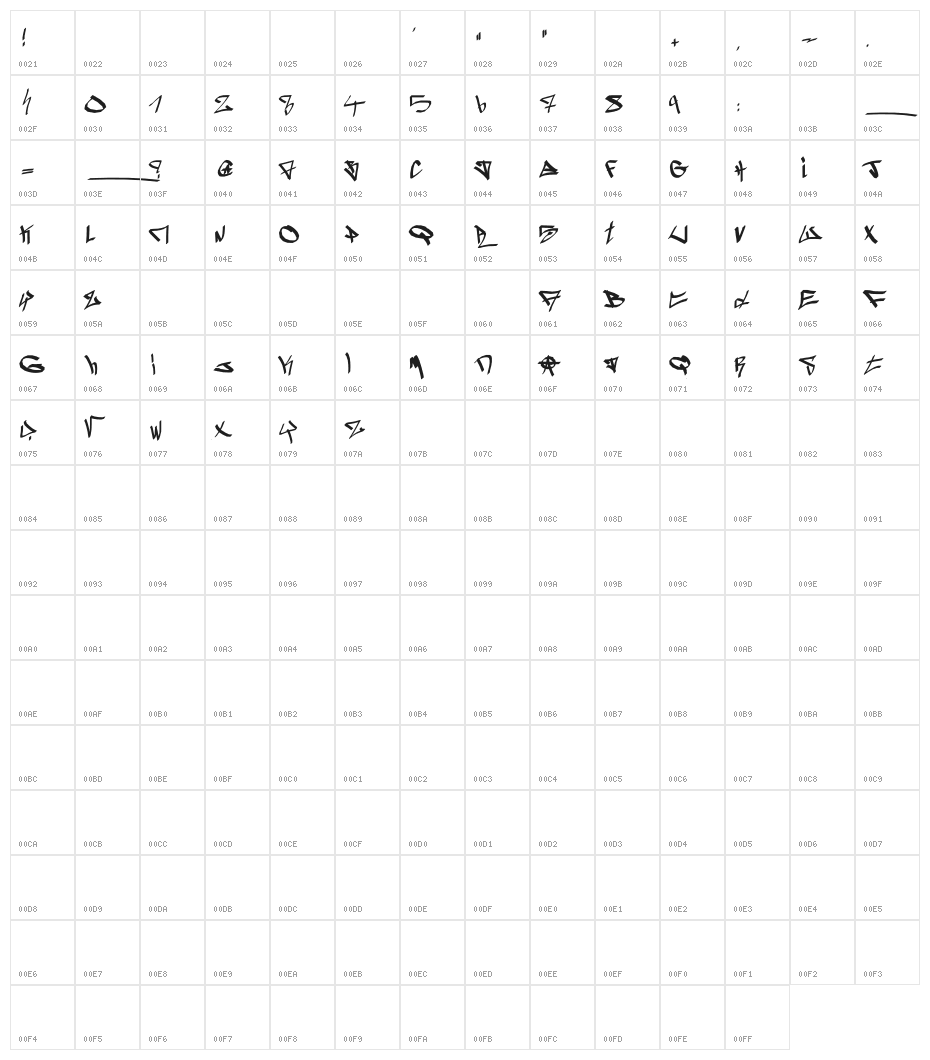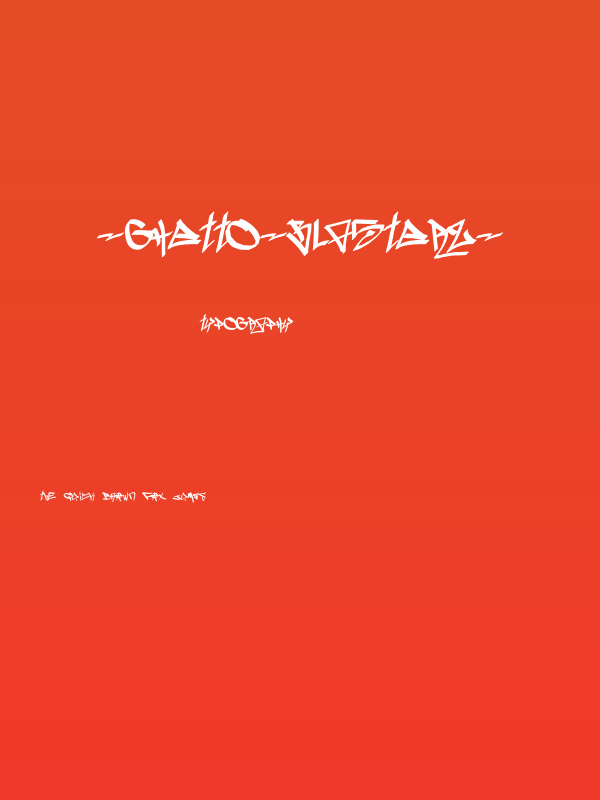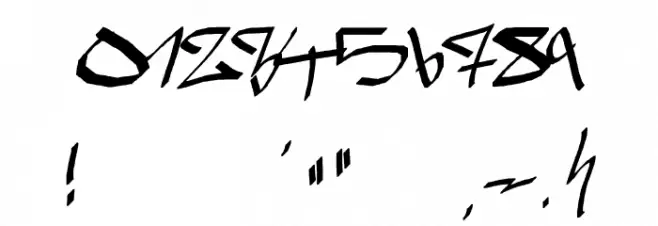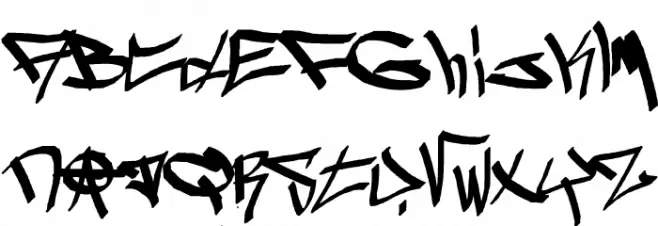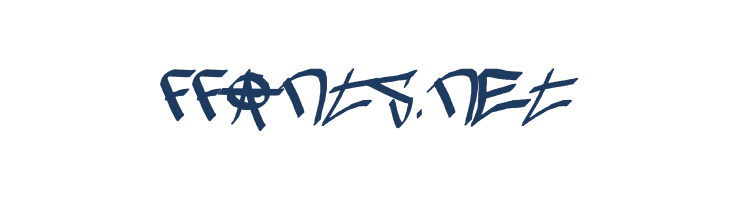
-ghetto-blasterz- Font
✎ Graffiti
| Stil general | Urban, Graffiti, Edgy |
| Caz de utilizare | Logos, Posters, Album Covers |
| Proiecte propuse | Ideal for street art designs, music album covers, urban-themed posters, and edgy branding projects. |